Die 36 besten Neon-Schriftarten 2023 (kostenlos und kostenpflichtig)
Veröffentlicht: 2023-05-10Sind Sie es leid, in Ihren Designs immer dieselben langweiligen Schriftarten zu verwenden? Möchten Sie Ihren Projekten einen Hauch von Farbe und Stil verleihen? Dann ist unser Artikel über die 36 besten Neon-Schriftarten genau das Richtige für Sie!
In diesem Artikel stellen wir einige der lebendigsten und auffälligsten Schriftarten vor, die das Design jedes Projekts mit Sicherheit verbessern werden. Von kräftig und kantig bis hin zu elegant und raffiniert gibt es für jeden die passende Neonschrift.
Wussten Sie, dass die Verwendung einzigartiger Schriftarten die Markenbekanntheit um bis zu 80 % steigern kann? Neon-Schriftarten ziehen nicht nur die Aufmerksamkeit des Lesers auf sich, sondern hinterlassen auch einen bleibenden Eindruck. Warum sollten Sie sich also mit dem Gewöhnlichen zufrieden geben, wenn Sie sich mit einer Neonschrift von der Masse abheben können?
In diesem Artikel erkunden wir die 36 besten Neon-Schriftarten, die sich perfekt dazu eignen, jedem Projekt einen Hauch von Persönlichkeit und Schwung zu verleihen.
Machen Sie sich bereit, Ihr Designspiel mit diesen atemberaubenden Schriftarten zu verbessern!
Beste Premium-Neon-Schriftarten
Suchen Sie nach Möglichkeiten, Ihre Designprojekte hervorzuheben? Möchten Sie Ihren Designs eine einzigartige Note verleihen, die Ihre Aufmerksamkeit erregt? Suchen Sie nicht weiter als nach den besten Premium-Neon-Schriftarten!
Neon Absolut
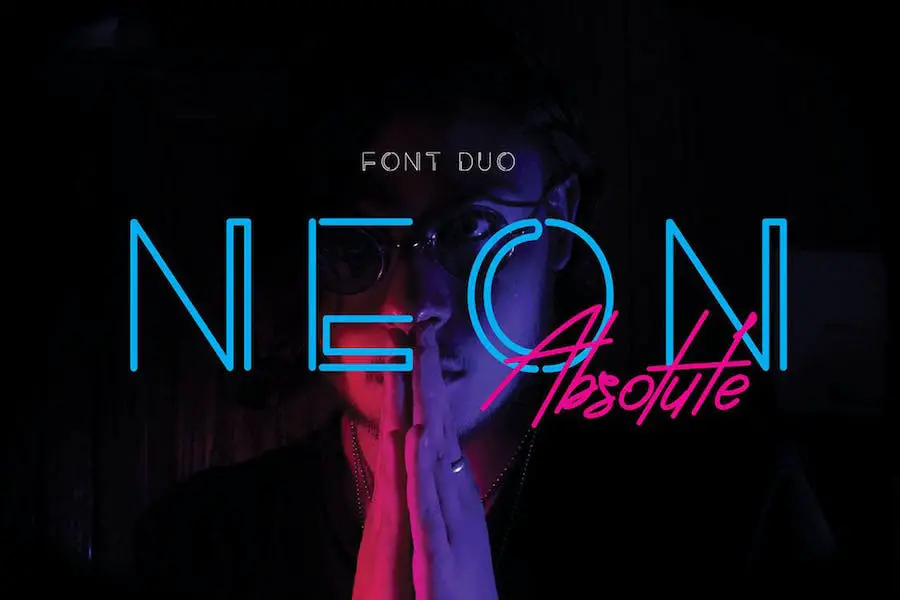
Neon Absolute ist eine Reihe stilvoller und moderner Schreib- und Sans-Schriftarten, die von den Neonlichtern und der 1980er-Jahre-Ära inspiriert sind. Dieses Schriftarten-Duo schafft eine perfekte typografische Balance für verschiedene Designprojekte wie Logos, Social-Media-Beiträge, Produktdesigns und Werbung.
Die Schriftart „Neon Absolute“ wirkt klassisch und zeitgemäß und eignet sich daher für jedes Designprojekt, das einen Hauch von Eleganz erfordert. Die Schreibschrift zeichnet sich durch fließende Linien und einen hervorragenden kalligrafischen Stil aus, der ein Gefühl von Flüssigkeit und Bewegung vermittelt, während die serifenlose Schriftart für ein klares und geradliniges Erscheinungsbild sorgt und sich ideal für Branding- und Schlagzeilendesigns eignet.
Gladiel
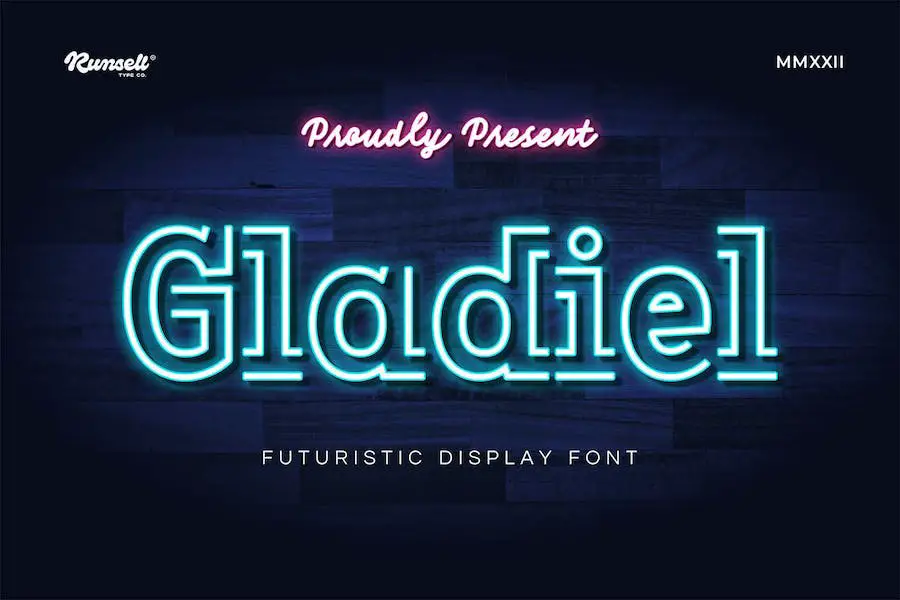
Gladiel Font ist eine vielseitige Ergänzung zum Arsenal jedes Designers und eignet sich perfekt für eine Vielzahl von Projekten, von Logos und Branding bis hin zu Zeitschriften und Websites. Mit Groß- und Kleinbuchstaben, Ziffern, Satzzeichen, mehrsprachiger Unterstützung und OpenType-Funktionen bietet Gladiel alles, was Sie zum Erstellen beeindruckender Designs benötigen.
Eines der herausragenden Merkmale von Gladiel ist seine Kompatibilität mit anderen Schriftarten. Sie können sie problemlos mit anderen Schriftarten kombinieren, um wirklich einzigartige und auffällige Designs zu erstellen. Egal, ob Sie ein auffälliges, aufmerksamkeitsstarkes Logo oder eine elegante, raffinierte Überschrift erstellen möchten, Gladiel hat das Richtige für Sie.
Newon
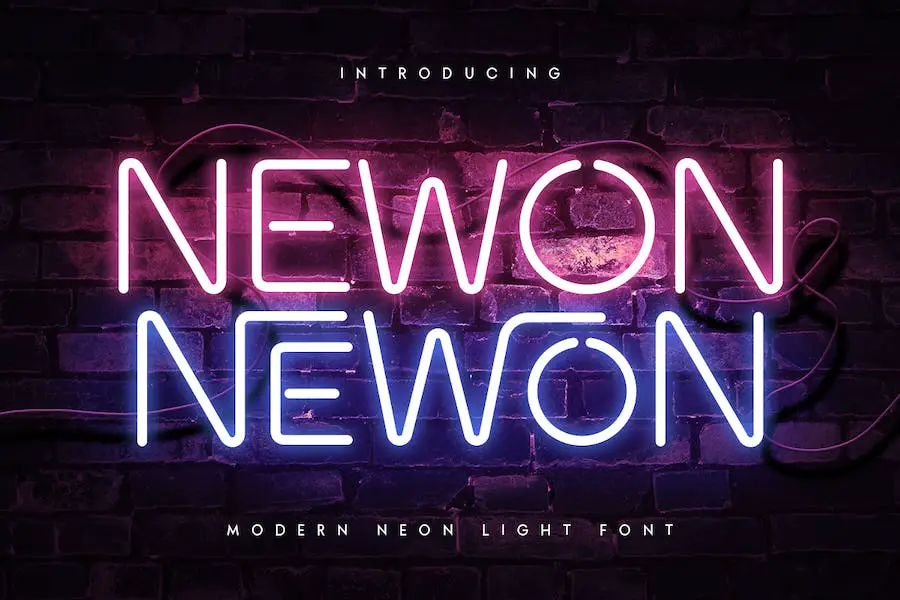
Newon ist eine Display-Schriftart, die speziell dafür entwickelt wurde, Ihre Überschriften und Titel durch ihren einzigartigen Stil und ihre moderne Ausstrahlung hervorzuheben. Es verfügt über zusätzliche Ligaturen, die es Ihnen ermöglichen, Ihre Variationen hinzuzufügen, was es perfekt macht, Ihren Projekten Ihre ganz persönliche Note zu verleihen.
Die Schriftart wurde sorgfältig gestaltet, um ein elegantes und modernes Aussehen zu erhalten, das zu jedem Projekt passt, an dem Sie arbeiten. Egal, ob Sie eine Website entwerfen, ein Logo erstellen oder an einer Zeitschrift arbeiten, Newon ist die perfekte Wahl für alle, die auffällige Schlagzeilen erstellen möchten.
Hastron
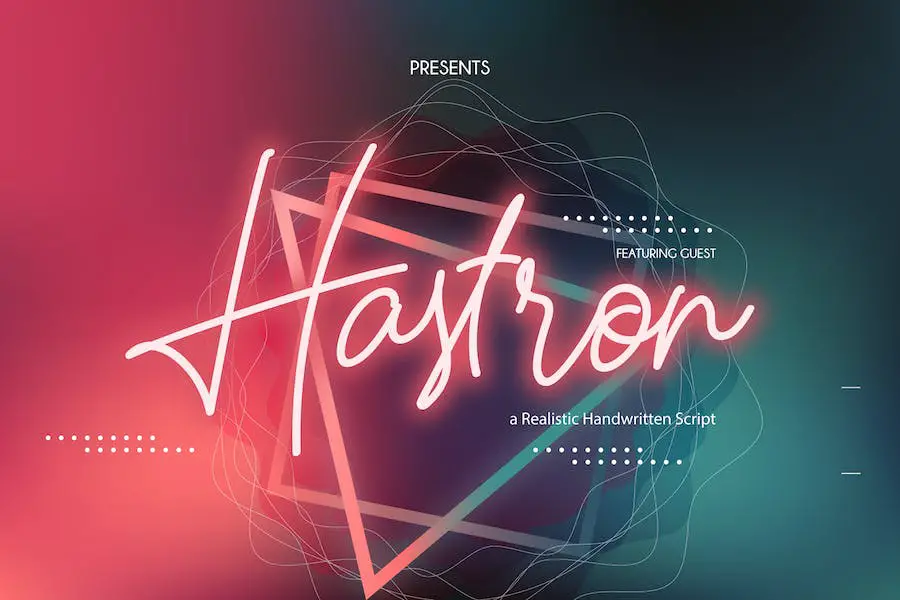
Hastron ist eine elegante neonfarbene Monoline-Schriftart, die sich durch einen wunderschönen Kalligraphiestil auszeichnet. Sein Design eignet sich perfekt für verschiedene Zwecke, z. B. zum Erstellen von Einladungen, Grußkarten, Branding-Materialien, Visitenkarten, Zitaten, Postern und mehr!
Aufgrund seiner einfachen Zugänglichkeit und seines vielseitigen Designs ist Hastron eine ausgezeichnete Wahl für Grafikdesigner, die ihren Projekten eine einzigartige und stilvolle Note verleihen möchten. Sein kalligraphischer Stil verleiht jedem Stück einen Hauch von Eleganz und hebt es von der Masse ab. Sie können in Ihrem Design auch Neon-Schriftarten für Word verwenden.
Fazit: Wenn Sie auf der Suche nach einer Schriftart sind, die Charme und Raffinesse ausstrahlt, sind Sie bei Hastron genau richtig. Ihre alternativen Zeichen und die Kompatibilität mit gängigen Designprogrammen machen sie zu einer fantastischen Wahl für Kreative, die eine Schriftart benötigen, die wirklich auffällt. Probieren Sie Hastron noch heute aus und bringen Sie Ihre Designs auf ein neues Niveau!
Neonlicht
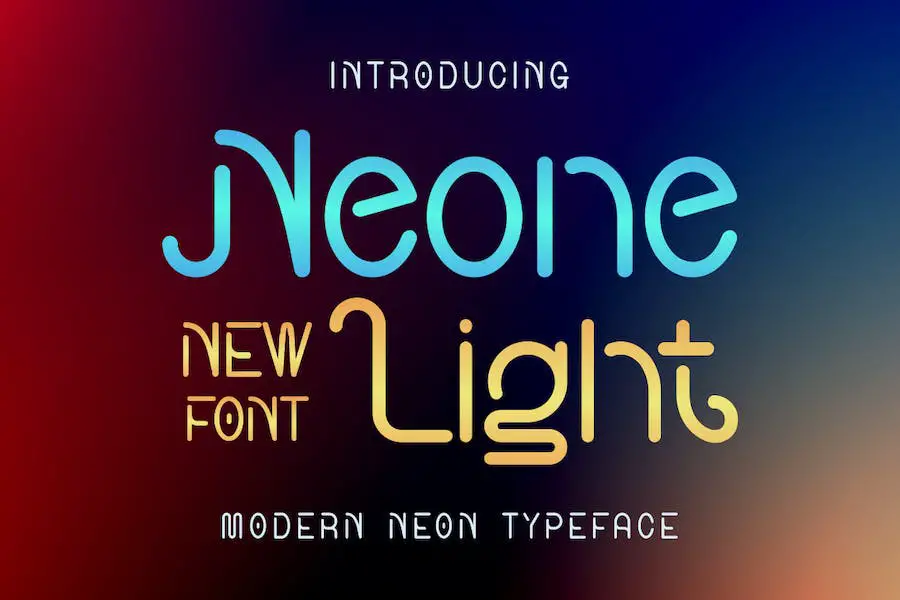
Neone Light ist eine neue moderne Schriftart, die jedem Designprojekt einen mutigen und authentischen Look verleihen kann. Diese Display-Schriftart eignet sich perfekt für Branding, Logoerstellung, T-Shirt-Druck und andere kreative Zwecke. Sein einzigartiger Stil sticht in einer Vielzahl von Umgebungen hervor.
Die Neone Light-Schriftart verfügt über mehrere Funktionen, die sie zu einer attraktiven Ergänzung für das Toolkit jedes Designers machen. Mit seinem auffälligen und auffälligen Erscheinungsbild wird es mit Sicherheit die Aufmerksamkeit der Betrachter auf sich ziehen. Die klaren Linien und das schlanke Design der Schriftart verleihen ihr ein modernes Gefühl und machen sie ideal für zeitgenössische Projekte. Darüber hinaus ist es vielseitig und kann in verschiedenen Kontexten eingesetzt werden.
Stacko Neon
Stacko Neon ist eine vielseitige Schriftart, die sich gut für verschiedene Designanforderungen eignet. Es hat einen verspielten und modernen Stil und eignet sich daher perfekt für die Verwendung in Logos, Branding, Werbedesigns, Cartoons, Animationen, Kinderbüchern, Leuchtreklamen, Postern, Zitaten, Buch- und Covertiteln, redaktionellen Designs, Websites oder Blogs, Karten und kundenspezifischen Designs Tassen, Kissen, T-Shirts und alle anderen handbeschrifteten Gegenstände.
Diese Schriftart verfügt über einen einzigartigen Neoneffekt, der jedem Projekt einen Hauch von Spannung verleihen kann. Die kräftigen und auffälligen Buchstaben erleichtern das Lesen, während die leuchtenden Farben eine energiegeladene Atmosphäre schaffen. Stacko Neon ist perfekt für alle, die sich mit ihren Designs von der Masse abheben möchten.
Ein weiteres großartiges Merkmal von Stacko Neon ist seine Lesbarkeit. Dank der klaren Linien und der fetten Buchstaben ist die Schriftart auch in kleinen Größen gut lesbar. Dies macht es perfekt für den Einsatz in Logos und Branding, wo es auf Lesbarkeit ankommt.
Konkretes Neon
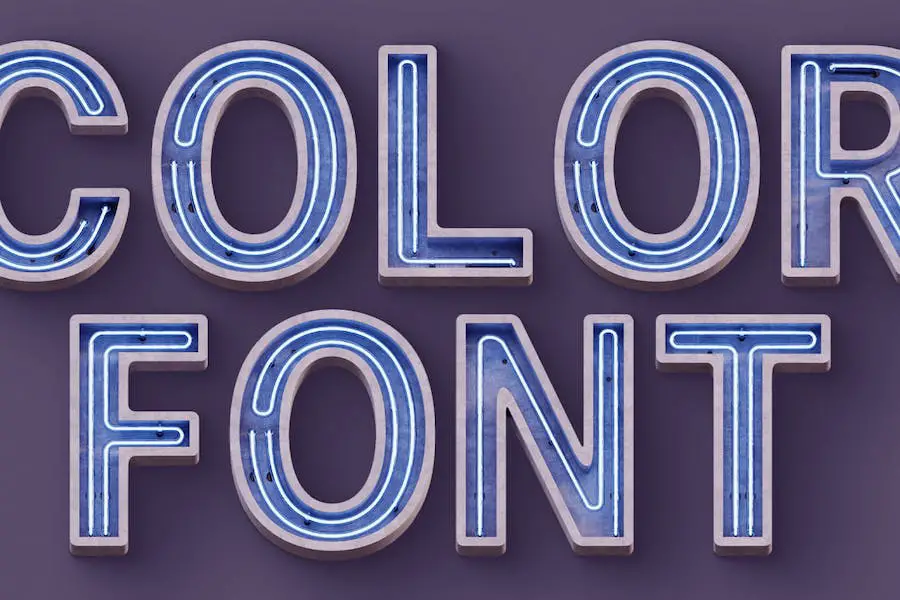
Concrete Neon ist eine einzigartige und auffällige Schriftart, die Ihren Designs einen urbanen, beton- und blauen Neon-3D-Stil verleiht. Diese Farb- oder SVG-OpenType-Schriftart funktioniert nur in Photoshop CC 2017+, Illustrator CC 2018 und einigen Mac-Apps.
Mit seinem kühnen und lebendigen Erscheinungsbild hebt Concrete Neon jedes Design hervor. Egal, ob Sie an einer Grafik für eine Website arbeiten oder ein Logo erstellen, diese Schriftart eignet sich perfekt, um ein Statement zu setzen. Sein 3D-Effekt verleiht ihm Tiefe und Dimensionalität und macht ihn wirklich unverwechselbar.
Eines der besten Dinge an Concrete Neon ist seine Vielseitigkeit. Es eignet sich perfekt für den Einsatz in einer Vielzahl von Projekten, von Werbe- und Marketingmaterialien bis hin zu Social-Media-Grafiken und mehr. Da es außerdem mit gängiger Designsoftware wie Photoshop und Illustrator funktioniert, lässt es sich leicht in Ihren Arbeitsablauf integrieren.
NACHTLICHT NEON – UMRISS
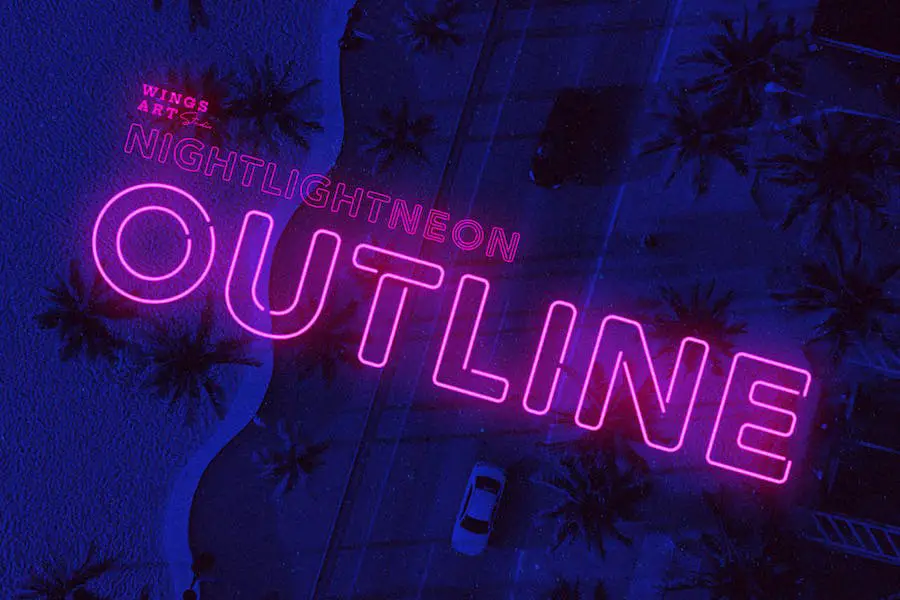
Night Light Neon – Outline ist eine Schriftart, die jedem Grafikdesign-Projekt einen Hauch von Neon verleihen kann. Mit dieser einzigartigen Schriftart können Designer das Erscheinungsbild handgefertigter Neonschriftzüge am Computer nachbilden.
Eine der herausragenden Eigenschaften von Night Light Neon – Outline ist die Fähigkeit, einen authentischen Neoneffekt zu erzeugen, ohne dass zusätzliche Software oder Plugins erforderlich sind. Die sorgfältig gestalteten Umrisse und Formen jedes Buchstabens ermöglichen eine einfache Anpassung und eignen sich somit perfekt für eine Vielzahl von Projekten.
Die Schriftart ist außerdem unglaublich vielseitig und kann in verschiedenen Umgebungen verwendet werden. Von Veranstaltungseinladungen bis hin zu Beschilderungen und allem dazwischen kann diese Schriftart jedes Designprojekt aufwerten. Darüber hinaus wird es mit seinen klaren Linien und kräftigen Formen jedem, der es sieht, ins Auge fallen.
Quilla Rachel
Quilla Rachel ist eine Monoline-Neon-Retro-Schriftart, die das Aussehen einer handschriftlichen Unterschrift nachahmt. Es ist vielseitig und kann in verschiedenen Designprojekten wie modernen Einladungen, Branding, Briefpapier, Blog-Design, Werbung, Hochzeitseinladungen und mehr verwendet werden.
Eines seiner herausragenden Merkmale ist sein einzigartiger Retro-Stil, der die Essenz von Neonlichtern aus der Vergangenheit einfängt. Sein Monoline-Design verleiht ihm eine klare und schlichte Ästhetik und eignet sich perfekt für moderne Designs. Ein weiteres Merkmal ist die handschriftliche Signatur, die jedem Designprojekt eine persönliche Note verleiht.
Quilla Rachel ist außerdem einfach zu verwenden und anzupassen, sodass Designer Größe und Farbe an ihre Bedürfnisse anpassen können. Seine Lesbarkeit und Klarheit machen es ideal für die Gestaltung von Buchumschlägen, Titeln oder Zitaten. Darüber hinaus eignet es sich zur Herstellung personalisierter Artikel wie individuell gestalteter Tassen, Kissen und T-Shirts.
Neonplanet
Neon Planet ist ein Schriftarten-Duo, das perfekt für alle ist, die ihrem Designprojekt eine moderne, futuristische Atmosphäre verleihen möchten. Mit ihrem neonförmigen Design und dem handgeschriebenen Stil mit Pinselstruktur hebt diese Schriftart Ihre Designs von der Masse ab. Es eignet sich für jedes Projekt, das ein Retro-, modernes oder lässiges Flair benötigt.
Eines der besten Dinge an Neon Planet ist seine Vielseitigkeit. Die Schriftart eignet sich gut für eine Vielzahl von Projekten, darunter Poster, Logos, T-Shirts und mehr. Darüber hinaus verleiht der handschriftliche Stil Ihren Designs eine persönliche Note, die mit anderen Schriftarten nur schwer zu erreichen ist.
Ein weiteres großartiges Feature von Neon Planet ist die Art und Weise, wie die Neonformen mit den übrigen Buchstaben interagieren. Durch die Kombination beider entsteht ein einzigartiger optischer Effekt, der garantiert ins Auge fällt. Egal, ob Sie für einen Nachtclub, eine Bekleidungsmarke oder etwas dazwischen entwerfen, diese Schriftart hilft Ihnen dabei, ein unvergessliches Design zu erstellen.
Neomarkt
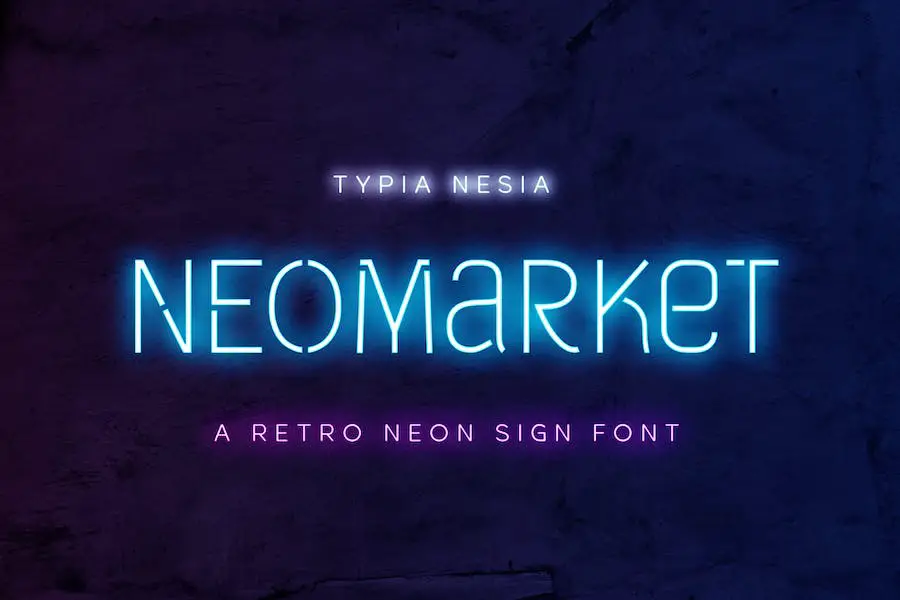
Neomarket ist eine vielseitige Display-Schriftart, die für eine Vielzahl von Designprojekten verwendet werden kann. Es eignet sich perfekt für Logo-Branding, redaktionelles Design, Briefpapierdesign, Sportdesign, Retro-Design der 80er Jahre, Spieleindustrie, modernes Werbedesign, Karteneinladungen, Kunstzitate, Heimdekoration, besondere Anlässe und vieles mehr.
Eines der herausragenden Merkmale von Neomarket ist seine Fähigkeit, eine Retro-Ästhetik hervorzurufen und gleichzeitig modern und frisch zu wirken. Die kräftigen, geometrischen Formen der Schriftart erinnern an klassische Leuchtreklamen und eignen sich daher ideal für Designs, die Aufmerksamkeit erregen und eine Aussage machen müssen. Sie können Leuchtreklame-Schriftarten für individuelles Design verwenden.
Ein weiteres großartiges Merkmal von Neomarket ist seine Vielseitigkeit. Sie ist in verschiedenen Stärken und Stilen erhältlich, von dünn und elegant bis hin zu dick und klobig, sodass Designer mit nur einer Schriftart eine Reihe unterschiedlicher Looks kreieren können.
Wiederholung
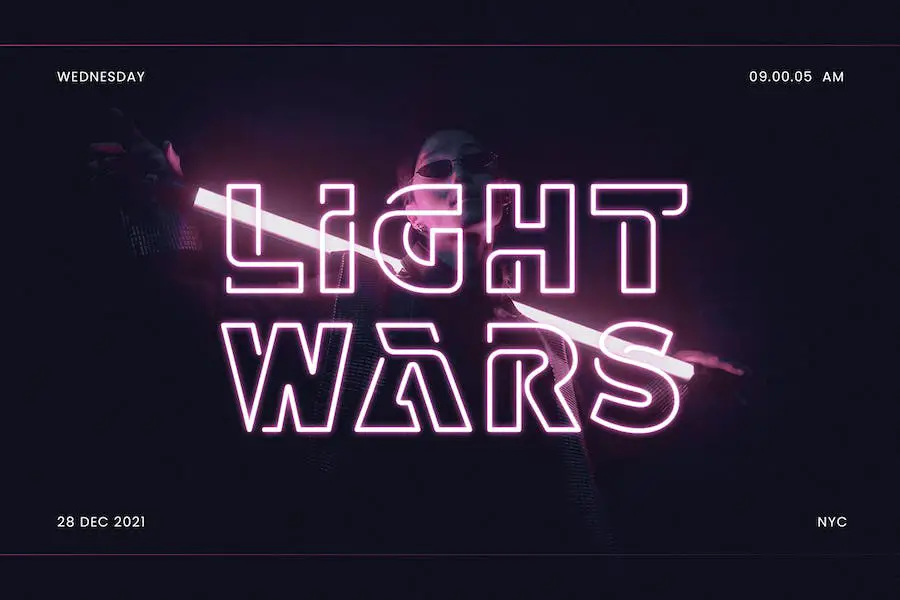
Retake ist eine unglaubliche Neon-Display-Schriftart, die Ihre Designprojekte auf die nächste Stufe heben kann. Wenn Sie nach einer Schriftart suchen, mit der Sie Ihre Logos, Anzeigen, redaktionellen Designs und Briefpapier hervorheben können, ist Retake die perfekte Wahl. Auch Neon Fonts Cursive können in Ihrem Design nützlich sein.
Diese Schriftart verfügt über eine Vielzahl von Funktionen, die Ihre kreativen Projekte zum Strahlen bringen können. Mit Retake können Sie atemberaubende Sportdesigns, 80er-Jahre-Retro-Designs, Grafiken für die Spieleindustrie, Musikplakate, Blog-Designs, moderne Werbung, Einladungskarten, Kunstzitate, Heimdekoration, Buch-/Covertitel, besondere Ereignisse und vieles mehr erstellen.
Sauvage
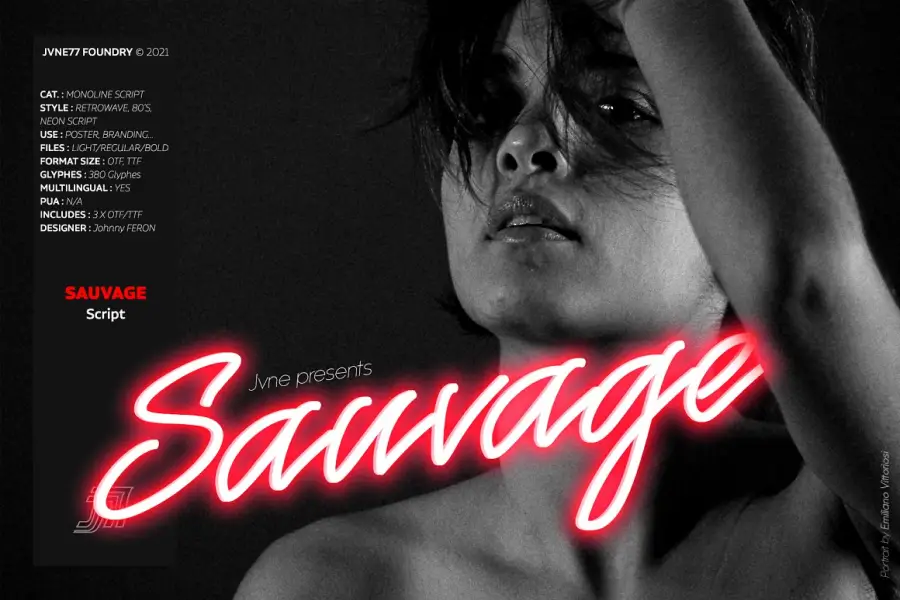
Sauvage ist eine Monoline-Schriftart, die sich perfekt dazu eignet, jedem Designprojekt eine stilvolle Note zu verleihen. Inspiriert von der klassischen ITC-Schrift, wurde es speziell für Neoneffekte entwickelt und kann auf Karten und anderen ähnlichen Projekten mit lateinamerikanischer Unterstützung verwendet werden.
Diese Schriftart bietet eine elegante und coole Ästhetik, die jedes Design hervorhebt. Der Monoline-Stil sorgt dafür, dass alle Linien gleich dick sind und Ihr Text im gesamten Design ein einheitliches Erscheinungsbild erhält.
Darüber hinaus sorgt der Skriptstil für ein klassisches und dennoch modernes Flair, wodurch es sich perfekt für eine Vielzahl von Designprojekten eignet.
Neon
Neon ist eine umfassende Sammlung von Schriftarten und Zeichen, mit denen Sie auffällige Neonschriftzüge für jedes Projekt erstellen können. Die Sammlung verfügt über eine beeindruckende Auswahl an Funktionen, die sich auf die beliebte Neon Tubes-Schriftart konzentrieren, die meistverkaufte Neon-Schriftart von Creative Market.
Zusammen mit der Schriftart finden Sie einen aufwendig detaillierten Neon-Texteffekt, ein Neonschild-Modell mit Anschlüssen und Kabeln sowie 24 schnell und einfach zu verwendende Neon-Photoshop-Ebenenstile.
Insgesamt ist Neon eine hervorragende Sammlung von Schriftarten und Zeichen, die sich perfekt für alle eignet, die professionell aussehende Neonschriftzüge erstellen möchten. Mit seiner breiten Palette an Funktionen und Anpassungsmöglichkeiten bietet es ein umfassendes Toolkit für die Erstellung von Neon-Beschilderungen, die mit Sicherheit beeindrucken. Ob Sie Grafikdesigner sind.
Neonröhren
Neon Tubes ist eine Schriftart, die von echten Neonlichtschildern inspiriert ist und mit schlanken Buchstabenformen und sanften Kurven aufwartet, um Projekten eine Retro-Atmosphäre zu verleihen. Das Besondere an dieser Schriftart ist, dass sie, genau wie echte Neonröhren, ausschließlich Linien mit offenen Start- und Endpunkten verwendet. Dadurch eignet es sich perfekt zum Entwerfen digitaler und physischer Leuchtreklamen oder zum Hinzufügen von Lichteffekten zu Ihren Designs.
Ein weiteres großartiges Merkmal von Neonröhren ist ihre Vielseitigkeit. Mit dieser Schriftart lassen sich verschiedenste Gestaltungselemente erstellen, von einfachen Logos bis hin zu komplexen typografischen Kompositionen. Durch seine klaren Linien und seine zurückhaltende Eleganz eignet es sich für eine Vielzahl von Stilen und Ästhetiken und ist somit ein Muss im Werkzeugkasten eines jeden Designers.
Sicherung
Fuse ist eine einzigartige dekorative Neonschrift, die von den tatsächlichen Neonlichtschildern auf den Straßen inspiriert ist. Die Schriftart zeichnet sich durch geometrische Buchstabenformen mit glatten abgerundeten Ecken aus und bleibt den echten Neonröhren treu. Diese Schriftart ist perfekt für alle, die ihren Designprojekten eine mutige und auffällige Note verleihen möchten.
Eine der besten Eigenschaften von Fuse ist seine Vielseitigkeit. Es kann für eine Vielzahl unterschiedlicher Projekte wie Musikwerbung, Filmtitel, Youtube-Tutorials, Konzertplakate, redaktionelle Verwendung, Logos, Beschilderungen oder einfach als fette Überschriften für Ihre Designprojekte verwendet werden. Die Möglichkeiten sind endlos und die Schriftart hinterlässt garantiert einen bleibenden Eindruck bei jedem, der sie sieht.
NEONBLITZ
NEONBLITZ ist eine neue Schriftart, die Ihrem Logo eine einzigartige Note verleihen kann. Der Retro-Neon-Fonts-Stil hebt es von anderen Optionen ab und ist von echten Neonlichtschildern inspiriert.
Die Schriftarten in NEONBLITZ haben minimale Buchstabenformen mit glatten abgerundeten Ecken. Die Designer hinter der Schriftart haben darauf geachtet, Linien mit offenen Start- und Endpunkten zu erstellen, genau wie bei echten Neonröhren. Mit dieser Liebe zum Detail können Sie Ihre eigenen leuchtenden Lichteffekte erzeugen oder sogar echte Neonschilder entwerfen.
Insgesamt bietet NEONBLITZ mit seinem von Neonlichtreklamen inspirierten Retro-Stil eine frische Interpretation von Schriftarten. Die minimalistischen Buchstabenformen und offenen Linien der Schriftart eignen sich perfekt für die Erstellung einzigartiger Designs mit Leuchteffekten. Für Designer, die ihren Projekten eine einzigartige Note verleihen möchten, könnte NEONBLITZ die perfekte Wahl sein.
Diskothek Neon
Discoteque Neon ist eine moderne kalligrafische Schriftart mit Electro-Retro-Flair. Es ist in zwei Versionen erhältlich – einer soliden OTF-Schriftart und einer Open SVG-Neon-Version, die Ihren Projekten lebendige Farben und einen auffälligen Glanz verleiht.
Die Standard-Volltonschrift ist mit allen Systemen kompatibel, während die Neonversion mit Schlagschatten und heller Beleuchtung für ein realistisches Aussehen sorgt. Diese künstlerische Schriftart kann in verschiedenen Projekten wie Postern, Logos oder Markenmaterialien verwendet werden.
Wenn Sie nach einer Möglichkeit suchen, Ihre Designs hervorzuheben, ist die Neonversion von Discoteque Neon eine gute Wahl. Die hinzugefügten Farben und Leuchteffekte verleihen Ihrem Projekt ein energiegeladenes und lebendiges Aussehen. Darüber hinaus verleiht es mit seinem kalligrafischen Schriftstil jedem Design einen Hauch von Eleganz und Raffinesse.
Buchtküste
Bayshore ist eine Schriftart, die Sie mit ihrem Retro-Monozeilen-Schriftstil in die Zeit der Neon-Schriftarten der 80er zurückversetzen kann. Es kann Ihrem Text ein cooles und stilvolles Aussehen verleihen, unabhängig davon, ob er für Logos, Produktverpackungen oder Waren verwendet wird.
Die Schriftartdatei verfügt über verschiedene Funktionen, mit denen Sie Ihren Text an Ihre Bedürfnisse anpassen können. Sie können die Dicke, Neigung und den Abstand jedes Buchstabens anpassen, um einzigartige Designs zu erstellen. Die handgezeichnete Textur der Buchstaben verleiht Ihren Projekten ein authentisches Vintage-Feeling.
Bayshore ist perfekt für Grafikdesigner, die eine Schriftart suchen, die vielseitig und einfach zu verwenden ist. Der unverwechselbare Stil dieser Schriftart macht sie ideal für die Erstellung auffälliger Designs, die sich von der Masse abheben. Mit ihrem Retro-Charme und ihrer modernen Funktionalität ist Bayshore eine Schriftart, die Sie mit Sicherheit beeindrucken wird.
Neonlinien
Neon Lines ist eine Schriftart, die von realen Schildern inspiriert ist, um eine klare und minimalistische Ästhetik mit geraden Linien und glatten abgerundeten Ecken zu schaffen. Im Gegensatz zu physischen Leuchtreklamen konzentriert sich Neon Lines auf die Schönheit des Minimalismus und eignet sich daher perfekt zum Hinzufügen leuchtender Lichteffekte zu Ihrem Text in Photoshop oder HTML/CSS.
Mit ihrem schlanken Design eignet sich diese Neonschrift perfekt für Ersteller von Online-Inhalten, die ihren Projekten einen modernen und auffälligen Touch verleihen möchten.
Ein weiteres großartiges Merkmal von Neon Lines ist, dass es sich problemlos in bestehende Designprojekte integrieren lässt. Es funktioniert nahtlos mit gängigen Designtools wie Photoshop und HTML/CSS und ist sowohl für Anfänger als auch für Profis mühelos zu verwenden. Darüber hinaus ist die Schriftart in mehreren Strichstärken verfügbar, was Designern noch mehr Flexibilität bei der Erstellung ihrer Projekte bietet.
Verkauf! Retrolicht
Retrolight ist eine Neonschrift, die Ihren Designs einen einzigartigen Retro-Touch verleiht. Diese Schriftart ist von realen Neonlichtschildern inspiriert und zeichnet sich durch klare Buchstabenformen mit glatten, abgerundeten Ecken aus. Getreu dem Neonröhrenstil werden ausschließlich Linien mit offenen Start- und Endpunkten verwendet. Sie können auch Neon Glow-Schriftarten verwenden.
Eines der besten Dinge an Retrolight ist seine Vielseitigkeit. Es eignet sich perfekt zum Hinzufügen eigener leuchtender Lichteffekte oder kann zum Entwerfen realer Leuchtreklamen verwendet werden. Mit dieser Schriftart können Sie wunderschöne Designs, Überschriften, Poster, Logos, Abzeichen, T-Shirts, Zertifikate, Etiketten und mehr erstellen.
Neon Farbe
Neonfarbe ist eine elegante und stilvolle Schriftart, die sich perfekt für die Erstellung auffälliger Designs eignet. Mit Großbuchstaben von A bis Z, Zahlen und Satzzeichen ist diese Schriftart vielseitig genug, um in verschiedenen Designprojekten verwendet zu werden. Darüber hinaus sind Neon Fonts für Figma perfekt für Sie.
Wenn Sie nach einer Schriftart suchen, die Ihre Casino-Etiketten, Schlagzeilen im Nachtleben, leuchtende Poster, Modekarten und andere Werbematerialien hervorhebt, ist die Neonfarbe auf jeden Fall einen Blick wert. Die kräftigen und lebendigen Neonfarben verleihen jedem Projekt einen Hauch von Eleganz und Glamour.
Eines der besten Dinge an der Neonfarbe ist ihre Lesbarkeit – auch bei kleineren Schriftgrößen bleibt die Schrift gut lesbar und angenehm für die Augen. Dadurch eignet es sich ideal für den Einsatz in digitalen Medien, wie zum Beispiel Websites und Social-Media-Beiträgen.
Outrunner
„Outrunner“ ist eine Retro-Schriftart, die Sie in die 80er-Jahre-Ära zurückversetzt. Die Schriftart wirkt klassisch und eignet sich für moderne und Vintage-Designs wie Signaturen, Logos, Branding, Einladungen, Blog-Schlagzeilen, Merchandise-Artikel und mehr.
Die Schriftart verfügt über OpenType-Funktionen und Alternativen, damit Sie die besten Ergebnisse erzielen. Wenn Sie Fragen zur Verwendung der Schriftart haben, wenden Sie sich unbedingt an den Verkäufer. Eine weitere Funktion dieser Schriftart ist die Verwendung von Neon Fonts Cursive in Ihren Projekten.
Zusammenfassend lässt sich sagen, dass „Outrunner“ eine gute Wahl ist, wenn Sie nach einer Schriftart mit Retro-Flair suchen. Seine OpenType-Funktionen und Alternativen machen es vielseitig und perfekt für eine Vielzahl von Designprojekten. Wenn Sie sich bei der Verwendung nicht sicher sind, zögern Sie nicht, den Verkäufer um Hilfe zu bitten.
Sternenschmiede
Starforge ist eine von Science-Fiction inspirierte Schriftfamilie, die sowohl im regulären als auch im Outline-Stil erhältlich ist. Es ist vollgepackt mit mehrsprachigen Großbuchstaben, alternativen Buchstabenoptionen (die mit der Feststelltaste ein- und ausgeschaltet werden können), Zahlen und Satzzeichen.
Mit seinen komplizierten Details ist Starforge perfekt für Grafikdesigner, die ihren Projekten einen Hauch von futuristischem Flair verleihen möchten. Das Science-Fiction-Thema fügt ein spannendes Element hinzu, das sich gut für Buchcover, Filmplakate oder sogar für Spieledesign eignet.
Abgesehen von der Ästhetik unterscheidet sich Starforge durch seine Vielseitigkeit von anderen Schriftarten. Mit den alternativen Buchstabenoptionen können Benutzer das Erscheinungsbild ihres Textes ändern, ohne eine völlig andere Schriftart verwenden zu müssen.
Beste kostenlose Neon-Schriftarten
In diesem Artikel stellen wir die besten kostenlosen Neon-Schriftarten vor, die im Internet verfügbar sind, und geben Tipps, wie Sie sie nahtlos in Ihre Designs integrieren können. Egal, ob Sie eine Visitenkarte, ein Website-Banner oder einen Social-Media-Beitrag entwerfen, diese Neon-Schriftarten werden mit Sicherheit die Aufmerksamkeit Ihres Publikums auf sich ziehen. Also lasst uns eintauchen und gemeinsam die Welt der Neon-Typografie erkunden!
Neons
Neons ist eine Demoversion von Neon-Schriftarten mit begrenzter Zeichenanzahl. Diese Schriftarten wurden speziell für Tattoo-Designs entwickelt, können aber auch in anderen Grafikdesign-Projekten verwendet werden, um eine einzigartige Note zu verleihen.
Die Neons-Schriftarten haben kräftige Linien und leuchtende Farben, die in jedem Design hervorstechen. Die Demoversion verfügt über eine begrenzte Zeichenanzahl, bietet aber dennoch genügend Möglichkeiten für kreative Gestaltungen. Jeder Buchstabe hat seinen eigenen einzigartigen Stil, der der Schriftart ein handgezeichnetes Aussehen verleiht.
Ein Vorteil der Verwendung von Neons ist seine Vielseitigkeit. Sie können es für eine Vielzahl von Designs verwenden, egal ob Sie ein Tattoo erstellen oder ein Logo entwerfen. Die kräftigen Linien und leuchtenden Farben machen in jedem Design Eindruck, während der handgezeichnete Stil eine persönliche Note verleiht.
Neonidas
„Neonidas“ ist die perfekte Schriftart, um Ihre Designs aufzuhellen und einen Hauch von Fröhlichkeit zu verleihen. Ob für eine Visitenkarte, ein Poster, eine Verpackung oder eine Einladung – diese Schriftart wird Ihr Design zum Hingucker machen.
Das neoninspirierte Design von „Neonidas“ erzeugt eine lustige und energiegeladene Atmosphäre, die mit Sicherheit die Aufmerksamkeit der Menschen auf sich ziehen wird. Die kräftigen und dicken Striche machen die Schrift aus der Ferne lesbar und eignen sich daher perfekt für Beschilderungen und Werbung.
Eine der besten Eigenschaften von „Neonidas“ ist seine Vielseitigkeit. Es kann für verschiedene Designprojekte verwendet werden, von der Schaffung eines Retro-Feelings bis hin zur Modernisierung einer Marke. Sein klares und klares Design macht es leicht zu lesen und eignet sich sowohl für gedruckte als auch für digitale Medien.
Neon Sans
Neon Sans ist eine einzigartige Schriftart, die den Vintage-Look handgefertigter Neonschriftzüge nachbilden soll. Mit dieser Schriftart können Designer ihren Projekten ganz einfach einen Hauch Retro-Glamour und eine elektrisierende Atmosphäre verleihen, ohne dass dafür spezielle Ausrüstung erforderlich ist. Auch Neon-Schriftarten für Circuit können für Ihr Design hilfreich sein.
Diese vielseitige Schriftart eignet sich perfekt für eine Vielzahl kreativer Anwendungen, von der Gestaltung von Musikwerbung und Filmtiteln bis hin zur Erstellung redaktioneller Layouts und auffälliger Logos. Egal, ob Sie fette Überschriften oder individuelle Beschilderungen erstellen möchten, Neon Sans bietet Ihnen endlose Möglichkeiten.
Las Enter
Die Las Enter-Schriftfamilie lässt sich außerdem einfach anpassen, sodass Sie Farbe und Größe an die Anforderungen Ihres Projekts anpassen können. Egal, ob Sie eine Retro-Leuchtreklame oder ein elegantes und modernes Design erstellen möchten, bei Las Enter sind Sie an der richtigen Adresse.
Wenn Sie nach einer Schriftfamilie suchen, die Ihr Projekt bei Google Neon Fonts hervorhebt, dann sind Sie bei Las Enter genau richtig. Sein einzigartiger Leuchteffekt und seine Vielseitigkeit machen es zur perfekten Ergänzung für den Werkzeugkasten jedes Designers. Warum also nicht Las Enter ausprobieren und sehen, wie es Ihre Designs auf die nächste Stufe heben kann?
Neon Zukunft 2
Neon Future 2 ist eine Display-Schriftart, die Sie auf eine retro-futuristische Reise mitnimmt. Diese Schriftart wurde in einem zeitlosen Stil entworfen, um Ihre Designprojekte hervorzuheben. Die Neon Future 2.0 Pro-Version enthält sieben verschiedene Schriftarten: Light, Regular, Regular Alternative, Bold, Regular Outline, Regular Alternative Outline und Bold Outline.
Die Neon Future 2.0 Pro-Version ist eine wesentliche Verbesserung der ursprünglichen Neon Future-Schriftart. Mit seinen sieben verschiedenen Schriftartvarianten bietet es Designern große Flexibilität bei der Erstellung einzigartiger und auffälliger Designs. Egal, ob Sie eine helle oder fette Schriftart, eine Outline- oder normale Schriftart benötigen, Neon Future 2.0 Pro bietet Ihnen alles, was Sie brauchen.
Diese Schriftarten sind perfekt für diejenigen, die Adobe Neon-Schriftarten zur Verbesserung ihrer Designprojekte suchen. Sie eignen sich hervorragend für Poster, Flyer, Logos und alle anderen Designs, die einen futuristischen und dennoch klassischen Look erfordern.
Stapler
Stacker ist eine Schriftart, die vielseitig und perfekt für eine Reihe von Projekten geeignet ist. Obwohl es sich nicht unbedingt um eine Monoline-Neonschriftart handelt, verfügt sie über Elemente, die sie zu einer hervorragenden Wahl für die Erstellung von Neoneffekten machen. Darüber hinaus ist Stacker aufgrund seiner starken Kernschrift ideal für den Einsatz in Visitenkarten der Technologiebranche und futuristischen Designs geeignet.
Eine großartige Sache an Stacker ist die Möglichkeit zur individuellen Anpassung. Obwohl die Schriftart selbst beeindruckend ist, lässt sie sich auch leicht an Ihre spezifischen Bedürfnisse anpassen. Unabhängig davon, ob Sie die Farbe oder die Form der Buchstaben anpassen möchten, kann Stacker ganz einfach an Ihre Anforderungen angepasst werden. Diese Flexibilität macht sie zu einer großartigen Option für Designer, die eine Schriftart benötigen, die sowohl funktional als auch anpassungsfähig ist.
Neon-Retro
Neon Retro ist eine atemberaubende Display-Schriftart, die Ihren Designprojekten die Schönheit realer Neonlichtschilder verleiht. Inspiriert von den einzigartigen Formen und Kurven von Neonröhren, verfügt es über kühne geometrische Buchstabenformen mit sanft abgerundeten Ecken, die ein Gefühl von Verspieltheit und Nostalgie ausstrahlen.
Eines der herausragenden Merkmale von Neon Retro ist seine Fähigkeit, bei einer Reihe von Designprojekten eine wunderschöne typografische Harmonie zu schaffen. Egal, ob Sie ein herausragendes Logo oder eine herausragende Markenidentität erstellen, auffällige Social-Media-Beiträge erstellen oder überzeugende Anzeigen und Produktverpackungen entwerfen möchten, diese Schriftart wird Sie mit Sicherheit beeindrucken.
Baletta
Baletta ist eine wunderschöne Schriftart im Signature-Stil, die den Charme echter Handschrift versprüht. Diese Schriftart ist ideal für Luxusmarken, Mode- und Schönheitsmarken, Künstler, Blogger, Social-Media-Beiträge, Hochzeitseinladungen und alle Projekte, die einen Hauch von Eleganz erfordern.
Mit seinen klaren Knoten und perfekten Ankerpunkten sorgt Baletta dafür, dass alle Striche und Kurven glatter sind und die Lesbarkeit verbessert wird. Es enthält einen vollständigen Satz an Groß- und Kleinbuchstaben im kyrillischen und englischen Alphabet sowie Ziffern, Satzzeichen und mehrsprachige Symbole. Die Ligaturen verleihen dem Gesamtdesign einen Hauch von Raffinesse und heben es von anderen Schriftarten ab.
Neonlicht
Neon Light ist eine Display-Schriftart, die Ihren kreativen Projekten ein mutiges und modernes Aussehen verleiht. Mit seiner futuristischen Ästhetik ist es perfekt für alle, die sich mit ihren Designs von der Masse abheben möchten. Auch Neon-Schriftarten für Canva können bei Ihrem Design nützlich sein.
Diese Neonschrift verfügt über eine Vielzahl von Funktionen, die sie zu einer großartigen Ergänzung für das Toolkit jedes Designers machen. Sein kühnes und auffälliges Erscheinungsbild wird mit Sicherheit Aufmerksamkeit erregen und jedem Projekt ein einzigartiges Flair verleihen. Die Schriftart ist vielseitig genug, um in den unterschiedlichsten Kontexten verwendet zu werden, von Werbekampagnen bis hin zu Social-Media-Grafiken.
Neonbines
Neon Bines ist eine vielseitige Schriftart, die für eine Vielzahl von Designprojekten verwendet werden kann, darunter Logos, Einladungen, Social-Media-Beiträge, Produktverpackungen und mehr. Seine Neon-Ästhetik verleiht jedem Design eine einzigartige Note und hebt es von der Masse ab.
Eines der herausragenden Merkmale von Neon Bines ist die große Auswahl an Zeichen, darunter Groß- und Kleinbuchstaben, Zahlen und Sonderzeichen. Dies erleichtert die Integration in jedes Designprojekt, ohne dass Sie sich Gedanken über fehlende Zeichen machen müssen.
Darüber hinaus ist Neon Bines in mehreren Strichstärken erhältlich, sodass Designer die Schriftstärke an ihre spezifischen Bedürfnisse anpassen können. Diese Flexibilität stellt sicher, dass die Schriftart problemlos sowohl für Überschriften als auch für Fließtexte verwendet werden kann.
Spac3 Neon
Spac3 Neon ist eine Schriftart, mit der Designer auffällige Designs erstellen können. Die gute Nachricht ist, dass es sich um eine kostenlose Schriftart handelt, sodass Sie sich keine Sorgen machen müssen, Geld auszugeben, um Zugriff darauf zu erhalten. Diese spezielle Schriftartendatei wurde auf Font Space entdeckt, einer großartigen Ressource zum Auffinden cooler Schriftarten.
Wenn Sie Spac3 Neon in Ihren Designs verwenden, haben Sie Zugriff auf eine einzigartige und aufmerksamkeitsstarke Schriftart, die Ihre Kunden und Kollegen mit Sicherheit beeindrucken wird. Egal, ob Sie Marketingmaterialien, Webdesigns oder Druckmaterialien erstellen, diese Schriftart hilft Ihnen dabei, Ihr Projekt auf die nächste Stufe zu heben.
Neonmagie
Neon Magic ist eine futuristische und moderne Display-Schriftart, die von Illushvara entworfen wurde. Diese Schriftart wird Ihr Projekt mit ihrem einzigartigen und auffälligen Design mit Sicherheit hervorheben. Es ist vielseitig und lässt sich problemlos in eine Vielzahl kreativer Projekte integrieren, was es zu einer ausgezeichneten Wahl für Grafikdesigner macht, die ihrer Arbeit einen Hauch von Magie verleihen möchten.
Das Design der Schriftart zeichnet sich durch einen faszinierenden Neoneffekt aus, der jedem Projekt eine lebendige und energiegeladene Atmosphäre verleiht. Es eignet sich perfekt für die Erstellung aufmerksamkeitsstarker Schlagzeilen, Logos und anderer Branding-Elemente, die eine Aussage machen müssen. Die klaren und schlanken Linien der Schriftart erleichtern das Lesen und stellen sicher, dass Ihre Botschaft effektiv kommuniziert wird.
Häufig gestellte Fragen
Neon-Schriftarten sind Schriftarten, die das helle, leuchtende Erscheinungsbild von Neonlichtern nachahmen. Sie werden häufig für Designs im Zusammenhang mit Nachtleben, Unterhaltung und Retro-Ästhetik verwendet.
Durch die Verwendung von Neonschriftarten können Sie Ihren Designs ein einzigartiges und auffälliges Element verleihen. Sie werden oft mit Aufregung, Energie und einer Retro-Ästhetik in Verbindung gebracht, was dazu beitragen kann, dass Ihre Designs hervorstechen und eine bestimmte Stimmung oder Emotion hervorrufen.
Es ist jedoch wichtig, Neonschriftarten sparsam und strategisch einzusetzen, da sie überfordernd wirken können, wenn sie übermäßig verwendet oder mit zu vielen anderen auffälligen Designelementen kombiniert werden.
Die Geschichte der Neonschriften lässt sich bis ins frühe 20. Jahrhundert zurückverfolgen, als Leuchtreklamen erfunden wurden. Diese Schilder wurden oft von erfahrenen Kunsthandwerkern handgefertigt, die Glasröhren in verschiedene Formen und Buchstaben biegen und sie mit Neongas füllen, um einen hellen, leuchtenden Effekt zu erzeugen. Im digitalen Zeitalter sind Neonschriftarten zu einer beliebten Möglichkeit geworden, diesen klassischen Look in einem zugänglicheren und vielseitigeren Format nachzubilden.
Abschluss
In diesem Artikel haben wir die 36 besten Neon-Schriftarten untersucht, die Ihre Grafikdesign-Projekte verbessern können. Wir haben verschiedene Stile und Designs besprochen, um Ihnen bei der Auswahl der perfekten Schriftart für Ihre spezifischen Anforderungen zu helfen.